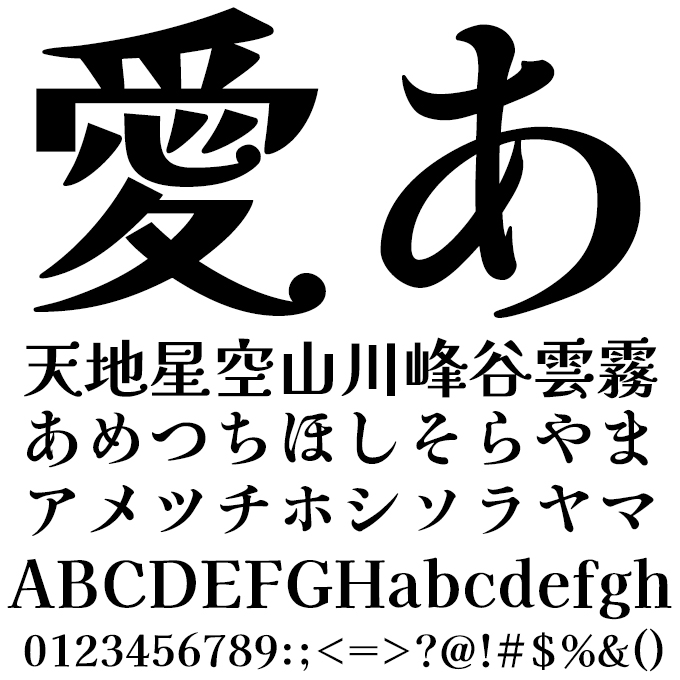
DSこだま
七種泰史/デザインシグナル
DSこだま
角ばった律儀なフォルムでありながら明るく軽やかな雰囲気をもつフォント。どこか懐かしく、心地よい暖かさを感じさせます。
DSバースディ19/21
七種泰史/デザインシグナル
DSバースディ19/21
文字のはいりの部分とトメの部分に筆圧を残し、枠にはとらわれない型にハマらないフォルム。優しい、素朴、楽しい、さまざまな表情を持った書体です。
DSユーミンウォーク
七種泰史/デザインシグナル
DSユーミンウォーク
のほほんとした雰囲気が緊張感を和らげ、やさしい表情を醸し出すウォークシリーズの中でも、丸みを帯びたシルエットが一層優しさを感じさせる書体。
DS歩明
七種泰史/デザインシグナル
DS歩明
よそ行きではなく、普段着を着た明朝体をイメージして作られたデザイン書体。アナログ感のある優しい雰囲気をまとったフォントです。
凛松体
楽フォント
凛松体
書道作品における毛筆の運びと墨によるダイナミックなウエイト表現にモダンなエッジを加えて、端正な面持ちの中にもしっかりとした芯が感じられるようにデザインしました。繊細な枝葉にそぐわず、荒々しく吹き付ける潮風をものともしない、凛々しい佇まいの黒松から着想を得ています。「雄松」とも呼ばれる黒松と同様、とどこか洒脱で伊達な男性的な力強さのある書体です。
辿秀体
楽フォント
辿秀体
丸くてゆるい雰囲気に、行書の章法とアートフォントの美感を融和した書体です。美しく洗練された自由気ままな線と字形の大小はまちまちで、全体的にリズム感を持たせています。また、古代書体の雰囲気があり、アート作品や個性的なブランドデザインのプロモーションなどに活用できます。